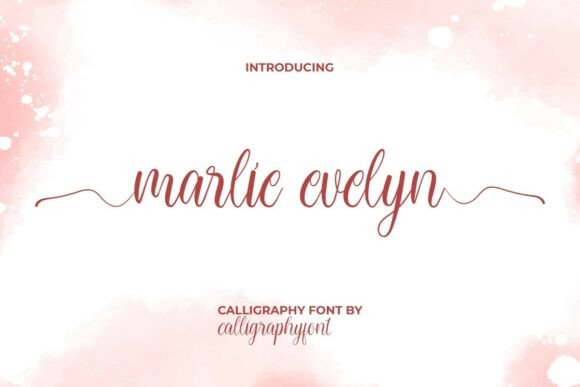
Marlie Evelyn
Jika anda sedang mencari aset berkualiti tinggi seperti Marlie Evelyn, pakej premium ini merupakan pilihan yang hebat untuk projek kreatif anda.
Dicipta dengan ketepatan, Marlie Evelyn menyediakan vektor yang bersih, tipografi yang licin dan lesen komersial untuk ketenangan fikiran.
Sama ada anda mencipta produk POD (Print on Demand), jemputan perkahwinan atau grafik media sosial, Marlie Evelyn amat bersesuaian.